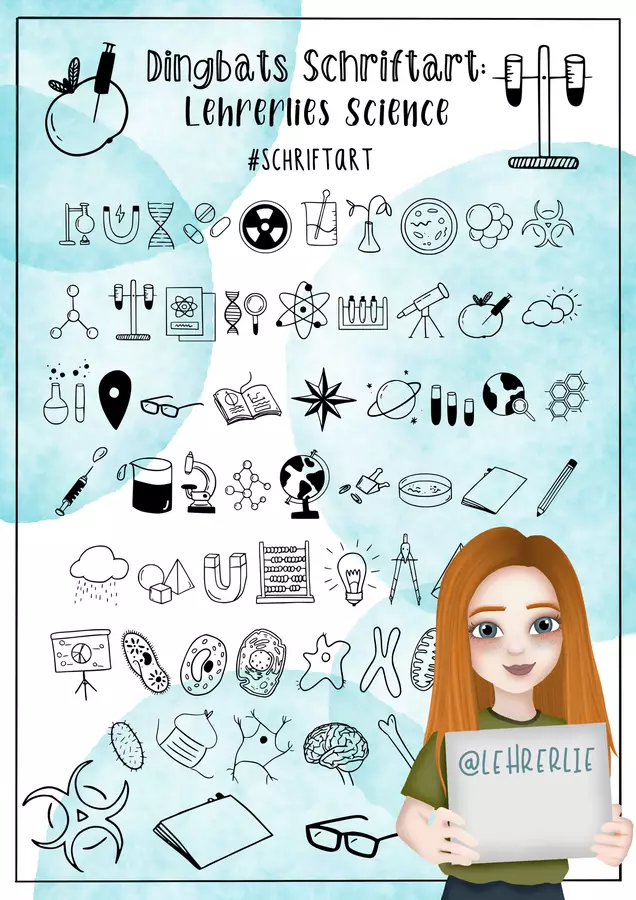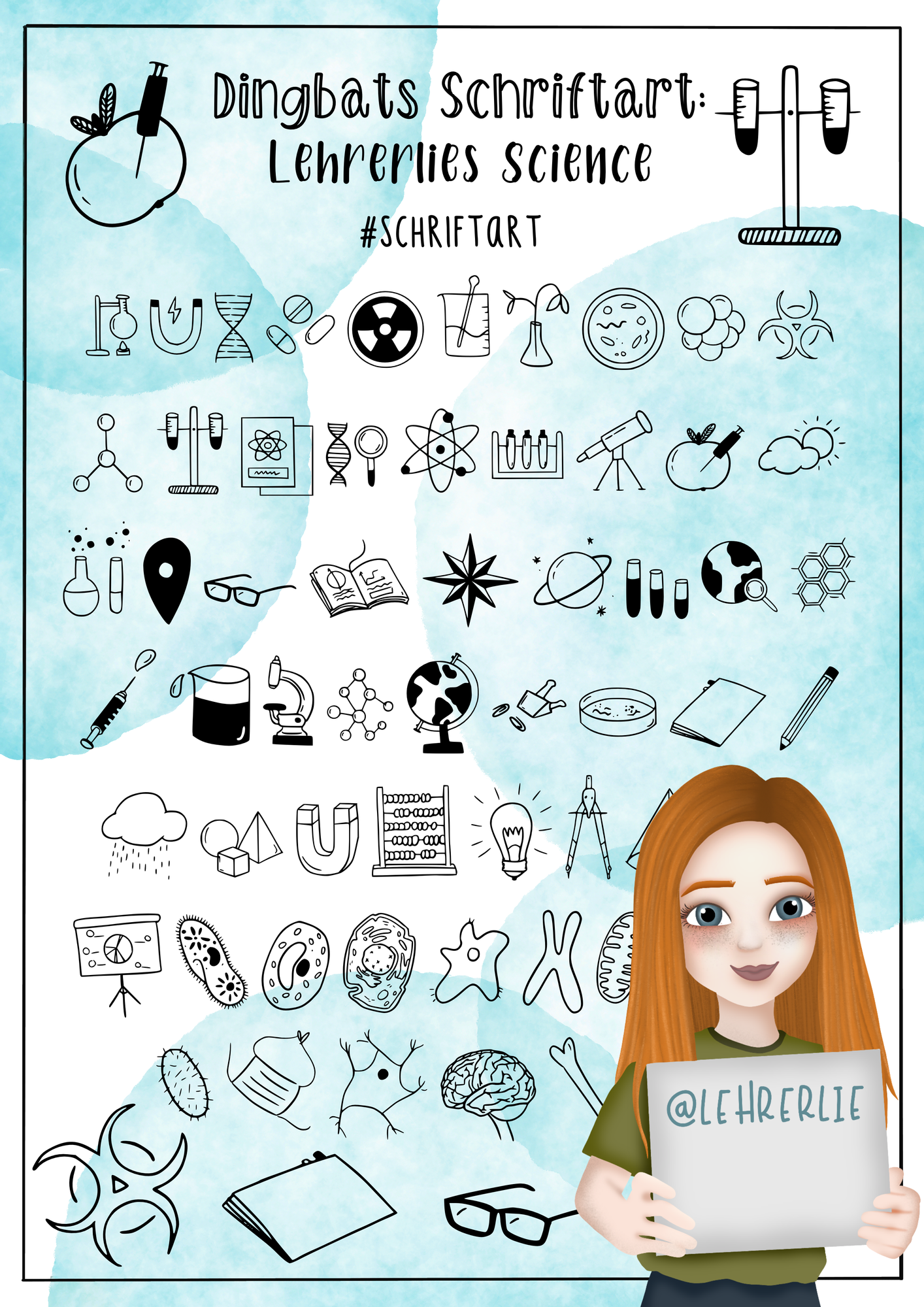
Hier bekommt ihr eine Symbolschriftart mit dem Thema Naturwissenschaft! :-) Ihr findet darin Symbole zum Thema Biologie, Chemie, Physik, Mathe und einiges anderes. Damit könnt ihr jedes Arbeitsblatt ganz einfach aufhübschen! Installiert die Dingbats einfach wie eine ganz normale Schriftart - und los gehts :-)
Dingbats-Schriftart: Lehrerlies Science